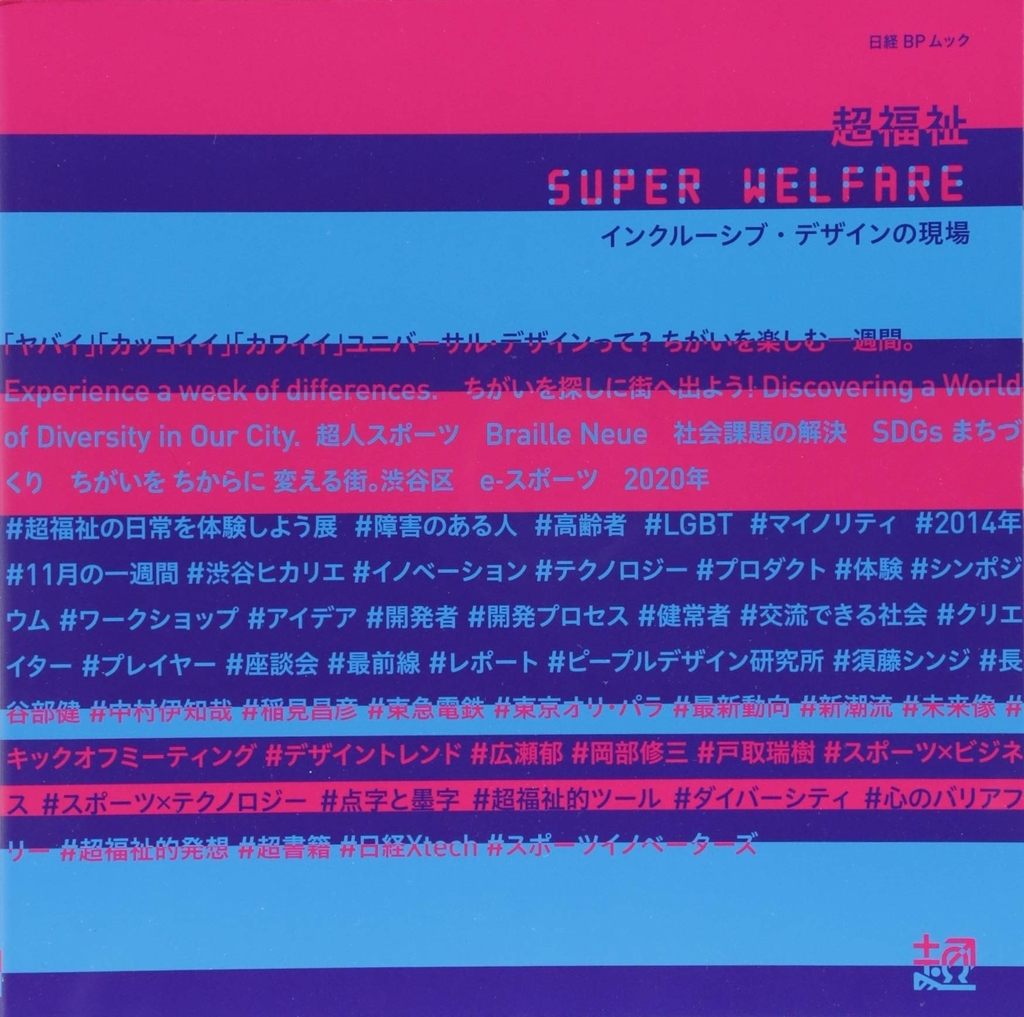
超福祉 SUPER WELFARE インクルーシブ・デザインの現場 (日経BPムック)
障害者やマイノリティと健常者が差別なく交流できる社会の実現をめざす「超福祉展(渋谷。超福祉の日常を体験しよう展)」で紹介されたアイデアやプロダクト、その開発の現場をレポートした「超福祉 SUPER WELFARE インクルーシブ・デザインの現場 (日経BPムック) 」が日経BP総研 社会インフララボ編集により日経BP社から2018年8月6日に発売された。
綴じ込み付録には、点字と墨字と組み合わせた世界初となる複合フォント「Braille Neue((ブレイルノイエ))」をムックとして初めて実装した。
Braille Neue(ブレイルノイエ)
「Braille Neue(ブレイルノイエ)」は、目が見える人でも目が見えない人でも同じ情報を一緒に読むことのできる点字であり、目で読める墨字と指で読める点字が一体になったユニバーサルな書体。
点字
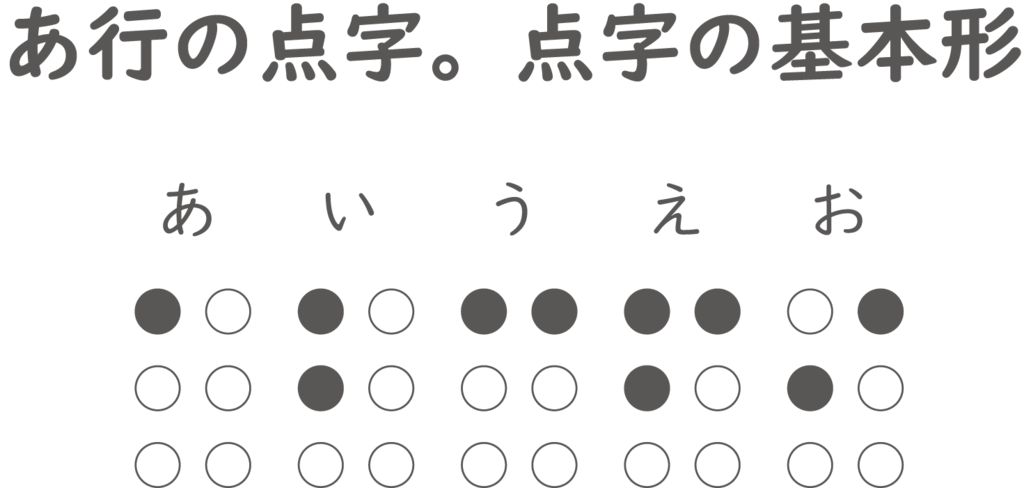
点字は平面から盛り上がった点で文字や数字を示した文字の表現方法。通常点字は、横2×縦3の6つの点で表されたブライユ(Braille)式点字が使用されている。
『超福祉展』(正式名称「2020年、渋谷。超福祉の日常を体験しよう展」)は、今年で5回目を迎えます。障害を抱えた人や、高齢者、LGBTなどのマイノリティ、福祉そのものに対する「心のバリア」を取り除こうと、2014年より毎年11月の一週間、渋谷ヒカリエを中心に渋谷の街全体で開催を続けている展示会です。
思わず「カッコイイ」「カワイイ」と使ってみたくなるデザイン、大きなイノベーションを期待させてくれるテクノロジーを備えたプロダクトの展示・体験に加え、魅力的なプレゼンターたちが登場するシンポジウムや多彩なワークショップなどで、従来の福祉の枠にとらわれないアイデアやプロダクト、その開発者や開発プロセスを数多く紹介してまいりました。従来の展覧会のイメージを“超えた"、まさに我が国で初めてのインクルーシブ・デザインの実践の場、といっても過言ではありません。
本ムックは、障害者やマイノリティと健常者が差別なく交流できる社会の実現をめざす同展で紹介されたアイデアやプロダクト、その開発の現場を集大成。超福祉に携わるクリエイターやプレイヤーによる座談会などを交えて、マイノリティーを巻き込みながら社会課題の解決を図るインクルーシブ・デザインの最前線をレポートします。また、長谷部渋谷区長や中村伊知哉慶應義塾大学教授といったキーパーソンのインタビューも掲載。 2020年の東京オリンピック・パラリンピックに向けた最新動向・新潮流もお伝えします。
"超福祉"はこれまでの障害者をはじめとするマイノリティへの偏見をなくし、“心のバリアフリー"を推進するインクルーシブ・デザインのお手本とも言える活動です。ダイバーシティの推進や社会課題の解決に向けて具体的に何をすればよいのか、これを目に見える形でわかりやすく伝える数少ないムックです。超福祉的発想に基づく本のデザインも、従来の書籍の概念を“超えた"ものとなっています。
主な内容
●特別インタビュー 長谷部健 渋谷区長 「すべてのちがいがまざり合い、自分たちで新たなものを創るまちへ」
まちをどのようにしたいと考え、何に着手しているのか。渋谷の未来像を語ってもらう
●巻頭レポート「超福祉展2018キックオフミーティング」
今年で5回目を迎える超福祉展、2018年はどんなチャレンジをし、何を飛び越えていくのか。2020年以降も見据えた超福祉の将来の姿を含めて展望する。
●クリエーターズ座談会「超福祉展に見るデザイントレンド」
超福祉展の主催者メンバーでもあるプロジェクトデザイナー広瀬郁氏、会場構成を担当する建築家・岡部修三氏、アートディレクター戸取瑞樹氏ら超福祉展を支えるクリエーターを一同に集めて座談会を開催。これまで様々な“概念や枠を跳び超えてきた"本展を振り返りつつ、超福祉展から見えてくるトレンドや将来に向けたビジョンを描き出す。
●特集 「超人スポーツ」
超人スポーツ協会が主催した第2回「超人スポーツゲームズ」の模様を詳細レポート。慶應義塾大学メディアデザイン研究科 中村伊知哉教授(博士)と東京大学 先端科学技術研究センター 身体情報学分野 稲見昌彦教授(工学博士)のインタビューを交えて、スポーツ×ビジネス、スポーツ×テクノロジーの最新動向を解説する。最近注目を集めるe‐スポーツの将来像についても言及した。
●綴じ込み付録『Braille Neue』
点字と墨字と組み合わせた世界初の複合フォント「Braille Neue」をムックとして初めて実装。視覚障害を持つ人と晴眼者のコミュニケーションが本を介して活性化する、新たな“超福祉的ツール"として提案する。